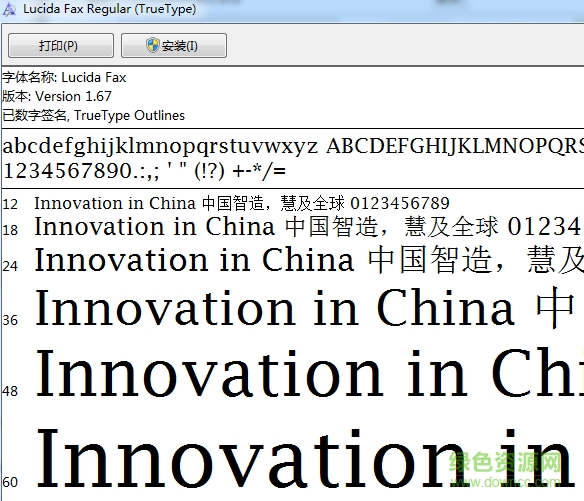
LUCIDAFAX字體是英文字體庫中的一款個性字體,該字體擁有很全面的字庫,讓從事平面設計的用戶能夠進行更全面的設計,多樣的字體凸顯廣告?zhèn)€性,需要的朋友不要錯過,趕快來綠色資源網(wǎng)下載使用吧!
LUCIDAFAX字體是一款字庫全面的英文字體,字體線條均勻,非常實用,看慣了一成不變的字體,就來綠色資源網(wǎng)試試這款不一樣的英文字體吧!